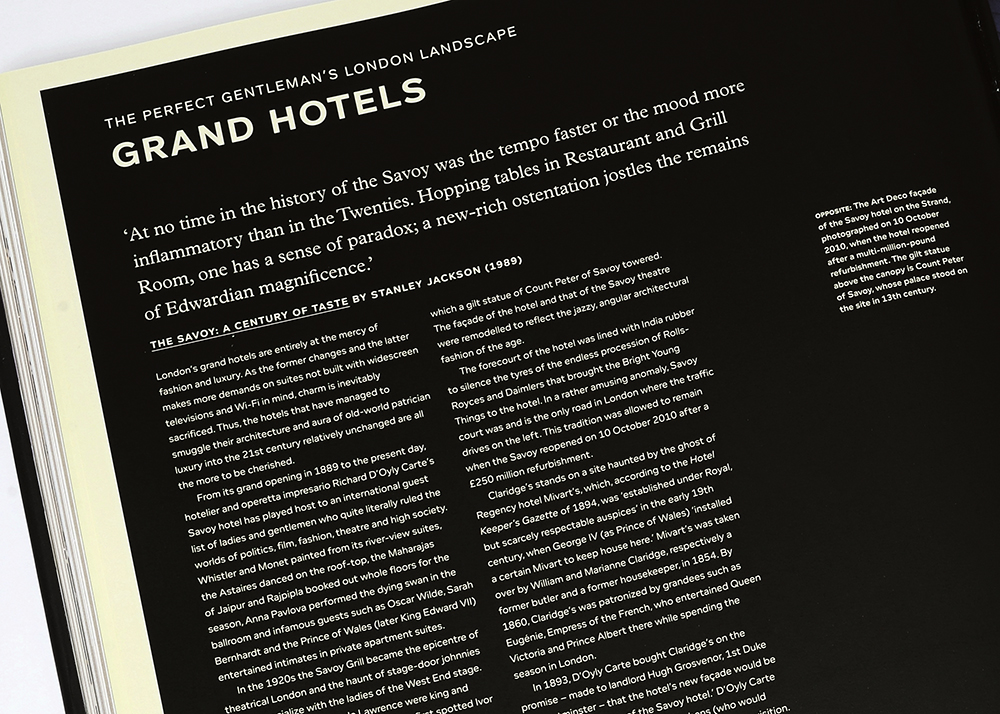
타이포그래피의 예술 : 타이포그래피 속성 강의
피터 도슨이 크기, 스타일, 위계에 관한 기본적이면서도 중요한 조언을 전한다.
결정, 결정, 그리고 또 결정. 활자 작업 과정에서 가장 중요한 열쇠는 최종 시안에 도달하기까지의 디자이너 혹은 타이포그래퍼의 수많은 결정이다. 크기부터 내용의 위계에 대한 이해까지, 디자이너는 모든 갈림길에서 올바른 선택을 내려야 한다. 이는 겉모습만 그럴듯한 작품이 아닌 보는 사람이 올바르게 이해하고 반응할 수 있는 작품을 짓기 위해서이다.
크기
본문 텍스트 작업을 할 때, 본문 텍스트의 왼쪽 끝부터 오른쪽 끝까지인 행간거리를 고려해야 한다. 행간길이가 너무 길면 읽기 어렵고 다음 줄로 넘어갈 때 집중력을 잃을 수 있다. 또한, 너무 짧으면 행 끝의 모양새가 좋지 않을 수 있고, 내용을 쉽게 받아들일 수도 없을 것이다. 가장 적당한 기준은 한 줄당 45에서 90개의 글자 수 정도라고 할 수 있다. 페이지의 크기를 고려한 후, 여백을 측정하고 앞에서 언급한 적당한 글자 수를 맞추어 크기를 조정하면 가독성을 최대한 높일 수 있을 것이다.
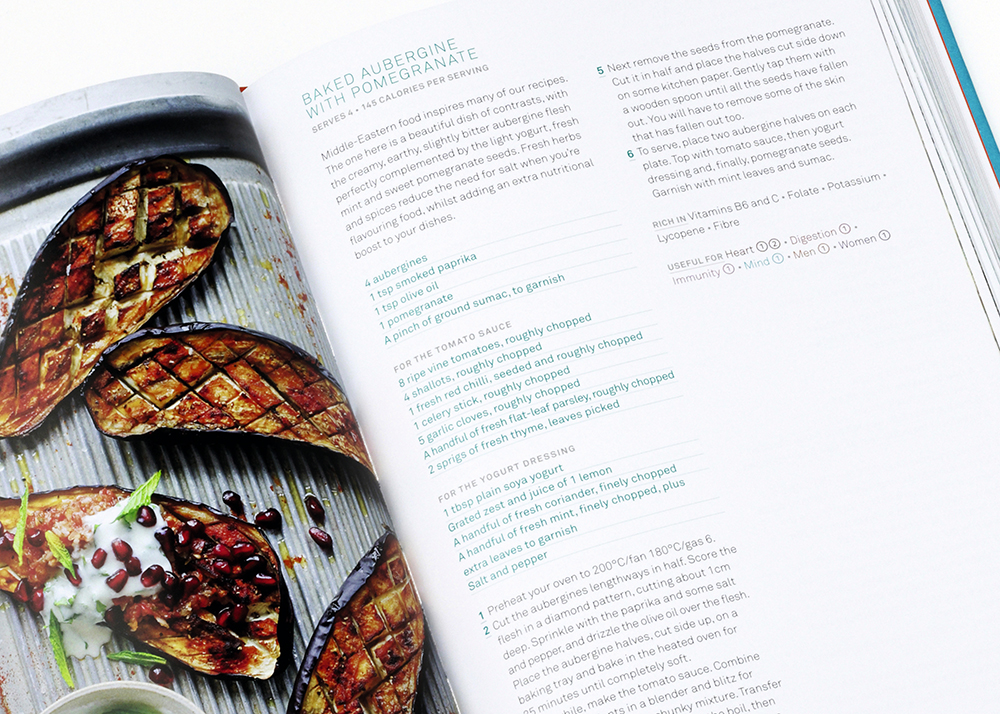
스타일
이탤릭은 본문에서 어떤 단어를 강조하거나 외국어 이름을 표기할 때, 혹은 출판물을 구분하고자 할 때 사용해야 한다. 나는 개인적으로 이탤릭으로 긴 본문이나 제목을 쓰는 것을 선호하진 않는다. 로만 타입이 훨씬 매력적이며 내용도 쉽게 읽힌다.
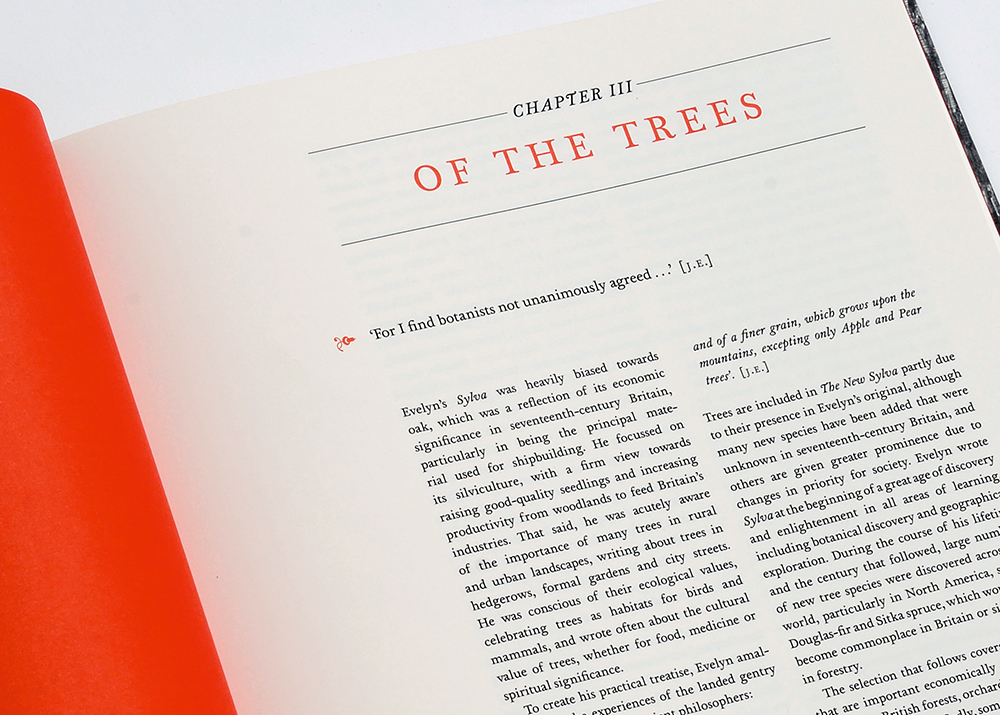
위계
처음 검토하는 원고라면, 텍스트의 양에 상관없이 구조의 개요를 구성하기 위해 내용을 훑어보는 것이 도움이 된다. 서체와 두께, 크기 결정을 위한 변수를 빠르게 이해하기 위해서는 인디자인에서 기본 서체만으로 페이지에 대충 얹어보는 것도 좋은 방법이다.